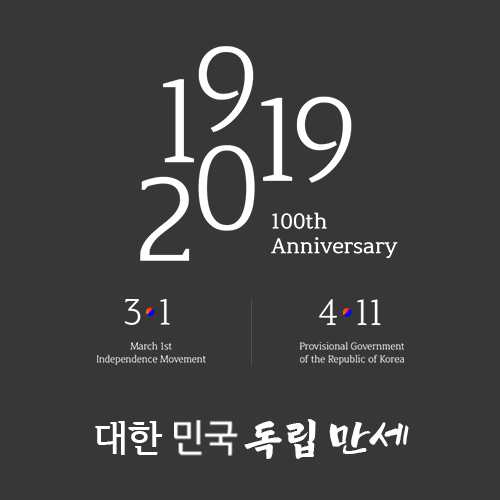
㈜윤디자인그룹, 3·1운동 및 대한민국 임시정부 수립 100주년 기념 서체 개발
㈜윤디자인 그룹이 대한민국 임시정부 수립 100주년을 맞아 ‘대한·민국·독립·만세’ 서체를 개발했다.
㈜윤디자인그룹이 대한민국 임시정부 수립 100주년을 맞아 ‘대한·민국·독립·만세’ 서체를 개발했다고 11일 밝혔다.
이번 3·1운동 100주년 기념 서체 개발은 ㈜윤디자인그룹에서 기획한 희망 프로젝트의 일환으로 지난 2013년 개발에 착수한 이후 7년에 이르는 제작기간 끝에 완성된 서체로 알려졌다.
독립운동 100주년을 맞은 올해, 윤디자인그룹은 선조들의 숭고한 얼을 기리고 우리글에 대한 긍지와 자부심을 자음과 모음 한자 한자 글꼴에 녹여냈다. 그리고 이를 함께 나누고자 대한민국 국민이라면 누구나 사용할 수 있도록 하였다.
최종 개발된 서체는 총 4종으로 그 중 ‘대한체’는 ‘전통의 처마지붕’을 모티브로 제작되었고 ‘민국체’는 ‘자유’와 ‘평등’을 모티브로 제작된 현대적인 고딕 서체이다. 대한민국임시정부가 발행한 기관지 ‘독립신문’의 한글제호를 복원한 ‘독립체’는 ‘독립을 염원하는 강한 의지’를 상징한다. ‘민초’를 상징하는 ‘만세체’는 민중이 하나가 되어 만들어낸 ‘만세의 물결’을 자유롭고 역동적인 캘리그라피 스타일로 표현하였다.